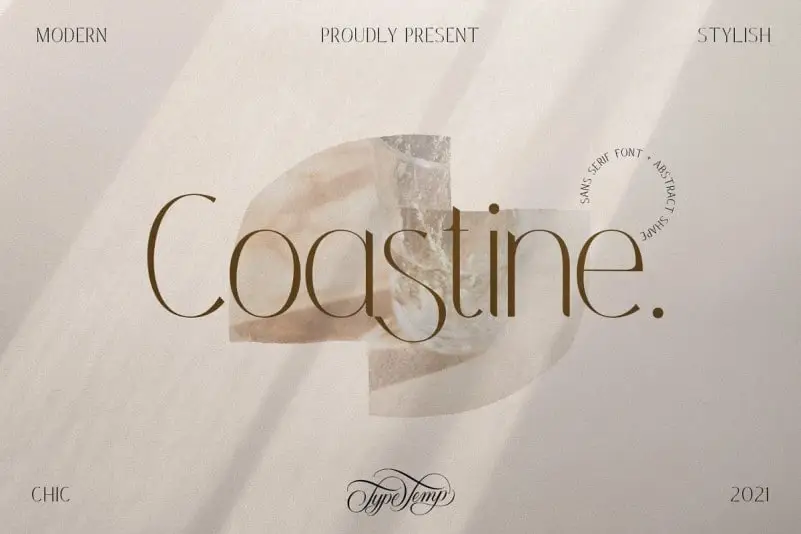
A fonte Coastine Sans Serif oferece aos designers uma variedade única e elegante para trabalhos editoriais, logos, rótulos de roupa, embalagens de produtos, cabeçalhos de revistas ou qualquer outro projeto que necessite de um texto suave e moderno. Com suporte multilíngue e ligaturas bonitas, essa fonte vem equipada com os recursos OpenType para acesso à seleção extensa de letras alternativas e ligações. Estes recursos permitem ao designer escolher as letras preferidas do grande conjunto disponível, resultando em uma exibição de texto que atende às suas necessidades específicas. Ideal tanto para projetos editoriais quanto para a criação de logos ou rótulos de embalagem, esta fonte é uma excelente adição à sua coleção de fontes, oferecendo um toque moderno e único a qualquer projeto gráfico.